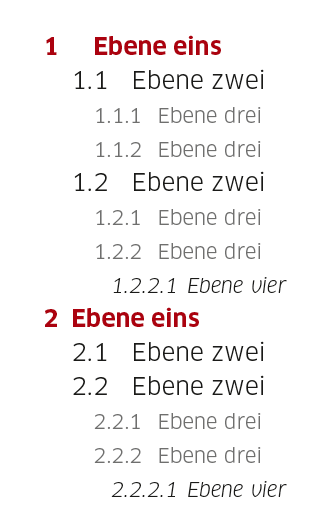
Nummerierte Liste/ Aufzählung
ich stehe momentan vor der Aufgabe, eine Variante einer nummerierten Liste/ Aufzählung überlegen zu dürfen. Habt ihr da irgendwelche Tipps, Best Practices, etc. wie sowas schön gestaltet aussehen könnte?
Word zeigt einem z.B. folgende Varianten:
1.
1.1.
1.1.1.
1.1.2.
1.2.
1.2.1.
1.2.2.
1.2.2.1.
etc.
Ich finde, diese Variante nimmt spätestens ab der 4. Ebene zuviel Platz weg.
Oder auch:
I.
A.
1.
2.
B.
1.
2.
a)
b)
etc.
Hier finde ich, dass bei der Nummerierung zu viele verschiedene Zeichen/Stile genutzt werden.
Aktuell bin ich bei dieser Variante stehen geblieben:
1)
a
1.
2.
b
1.
2.
a
b
etc.
Also ein logisches System, bei dem immer abwechselnd Zahlen und Buchstabenreihen genutzt werden, wobei die 1. Ebene durch die geschlossene Klammer und die 3. Ebene durch den Punkt hinter der Nummer besonders hervorgehoben werden.
Wie sind eure Ideen/Vorschläge?
Wenn die Aufzählung logisch und (ein)eindeutig sein soll, dann kann dies meiner Meinung nur Variante 1 und mit abstrichen Variante 2 gewährleisten. Bei Variante 3 ist die hierarchische Zuordnung nicht klar definiert.
Sehe ich auch so. Noch eine Ergänzung:  Hinter die jeweils letzte Ziffer (also auch bei 1 und 1.1) gehört kein Punkt.
Ihr habt Recht: meine Formatierung ist insofern nicht logisch und eineindeutig, wenn man einen Punkt rausgreifen und zitieren möchte. Variante 1 ist mir allerdings irgendwie noch zu klobig.
@Dieter: Word sieht das übrigens anders, aber das ist ja auch keine wirkliche Referenz ;o)
Du hast noch mehr Gestaltungsmöglichkeiten als nur Einzüge …